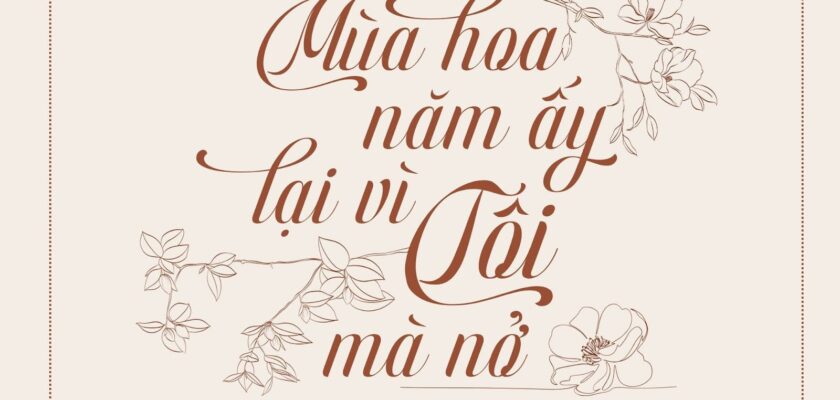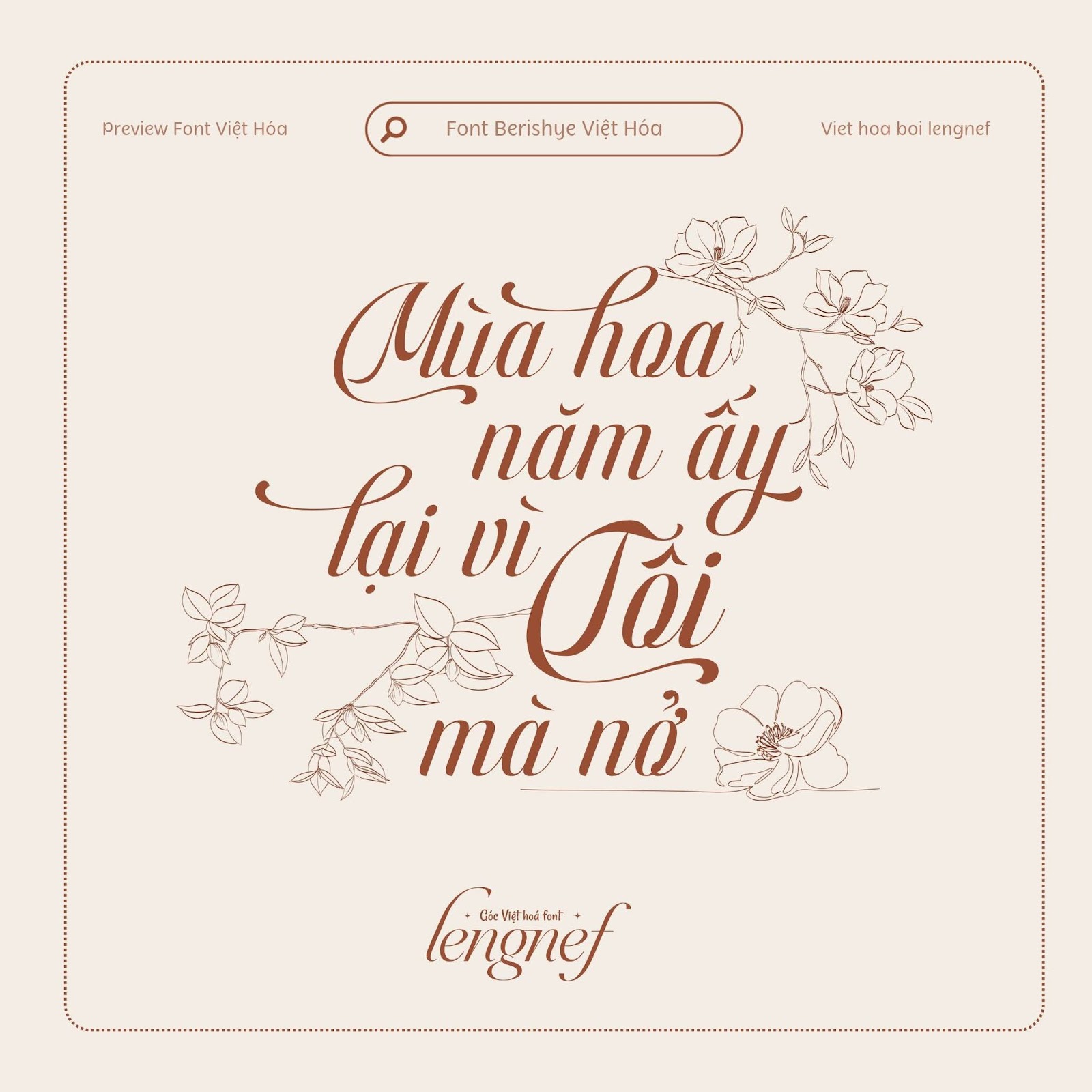
• Tác giả: Timeless Type
• Việt hóa: lengnef
Font LF Berishye
Berishye – tiếp tục là một phông đến từ Timeless Type. Một kiểu phông chữ script với nhiều glyph uốn lượn rất phù hợp cho thiệp cưới, logo, các dự án bìa sách, nhạc…